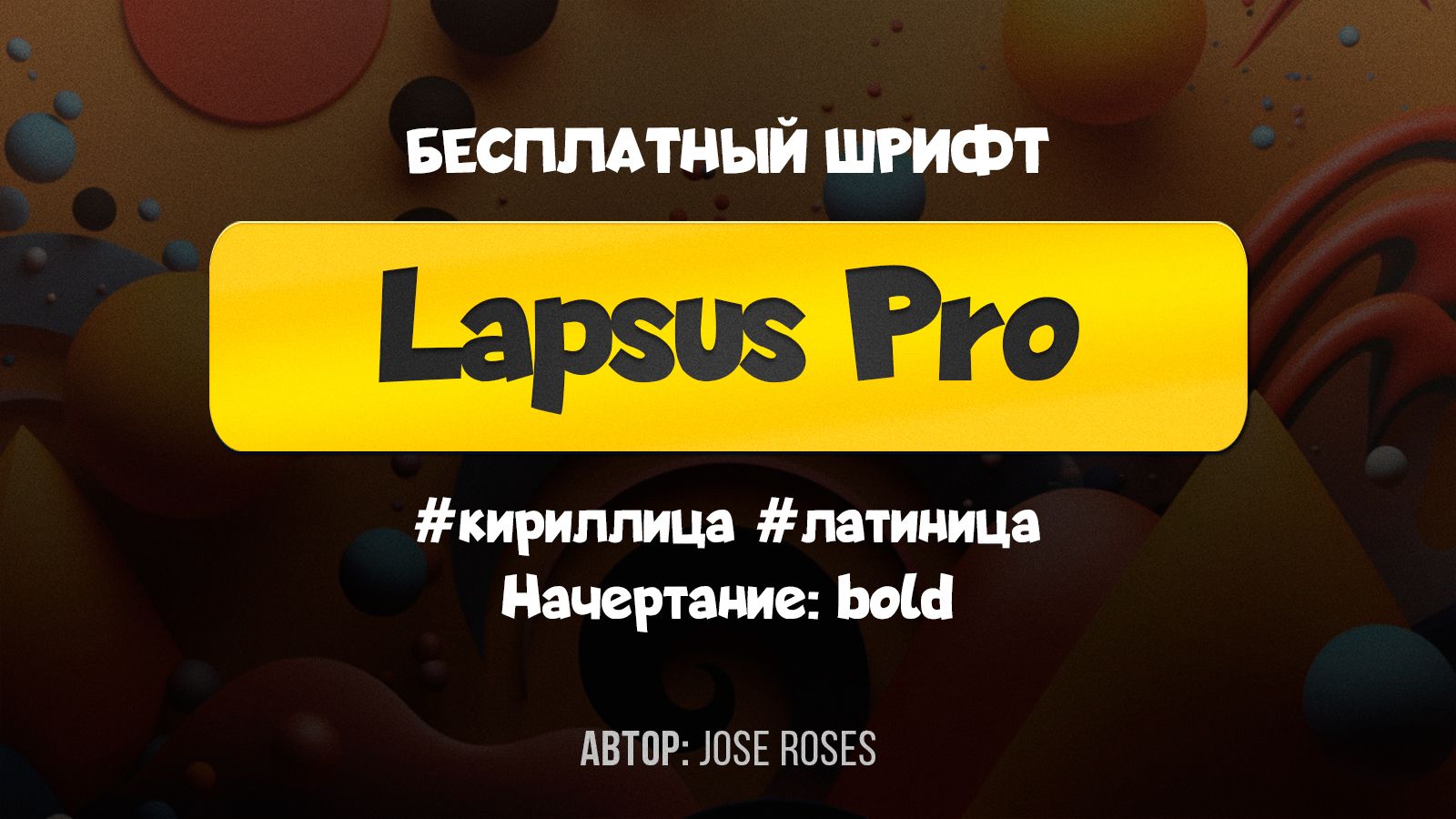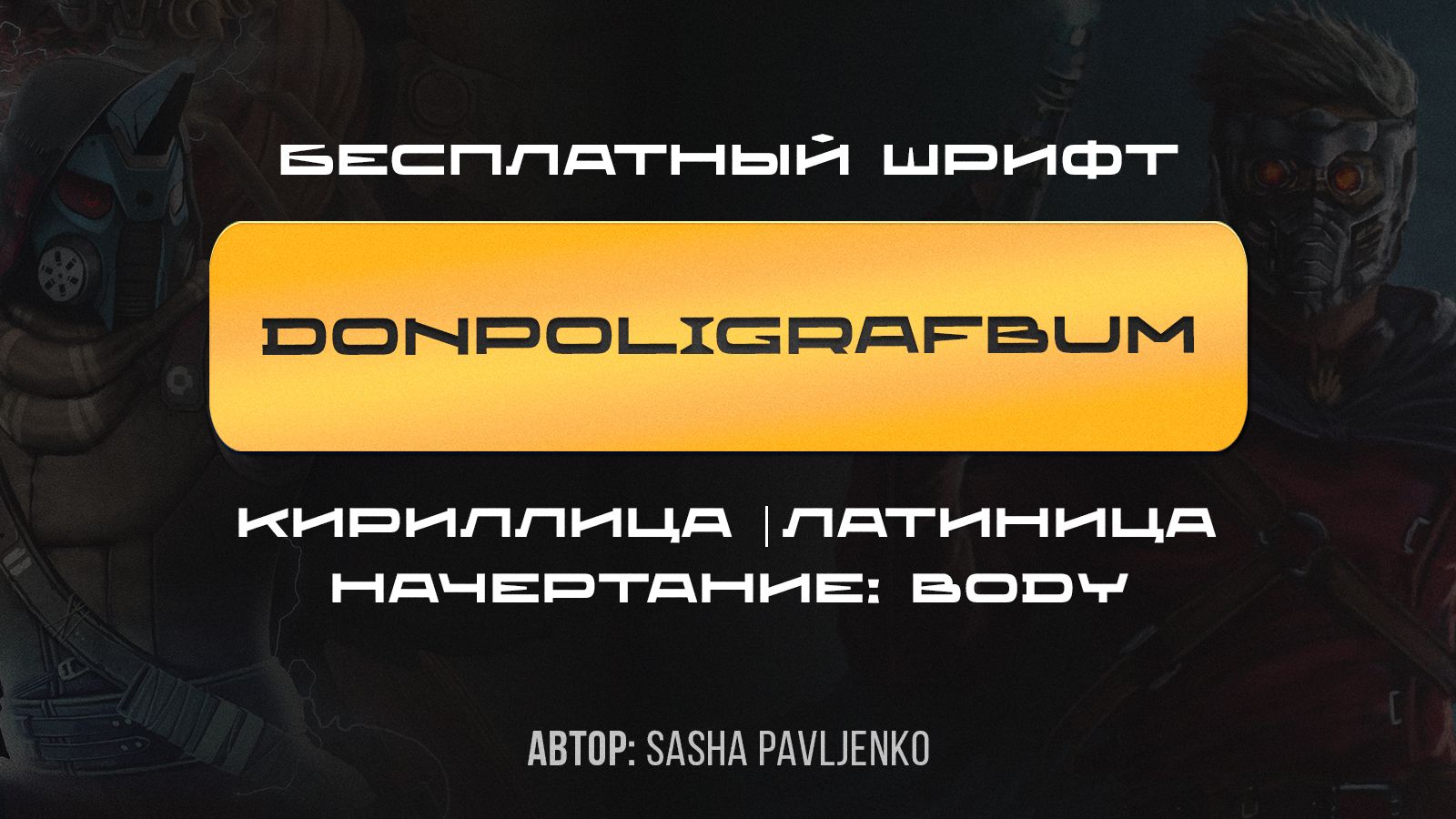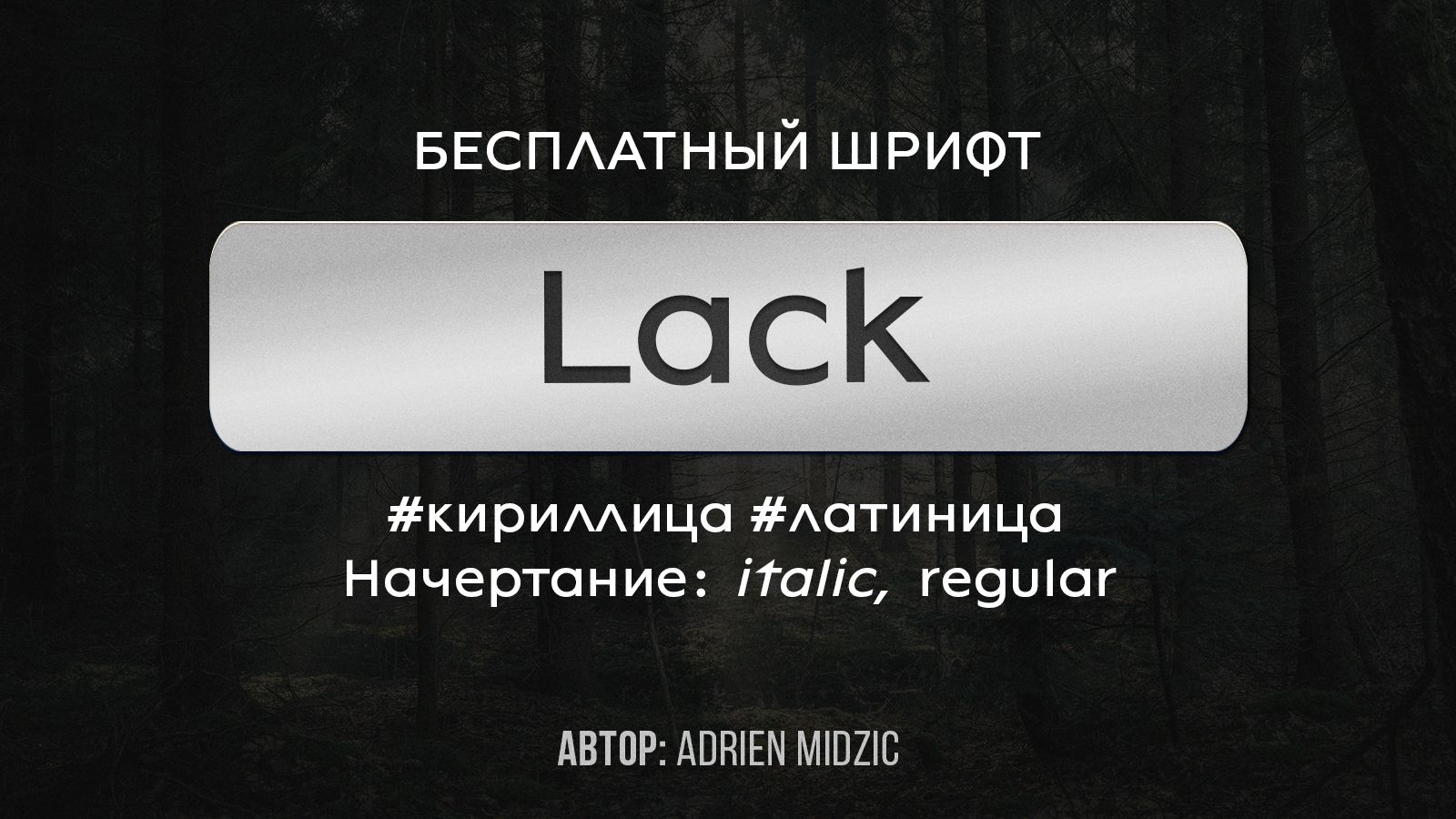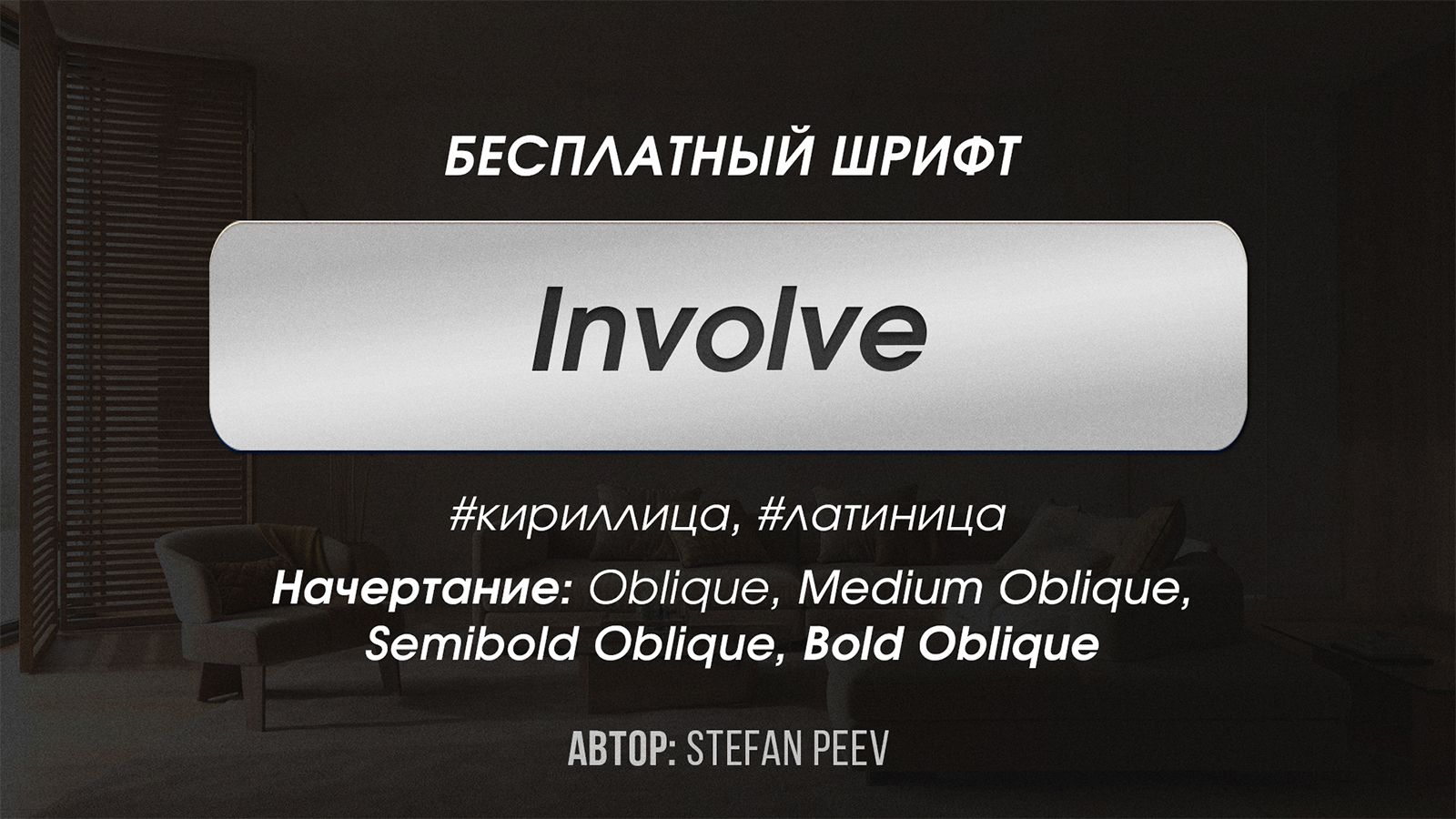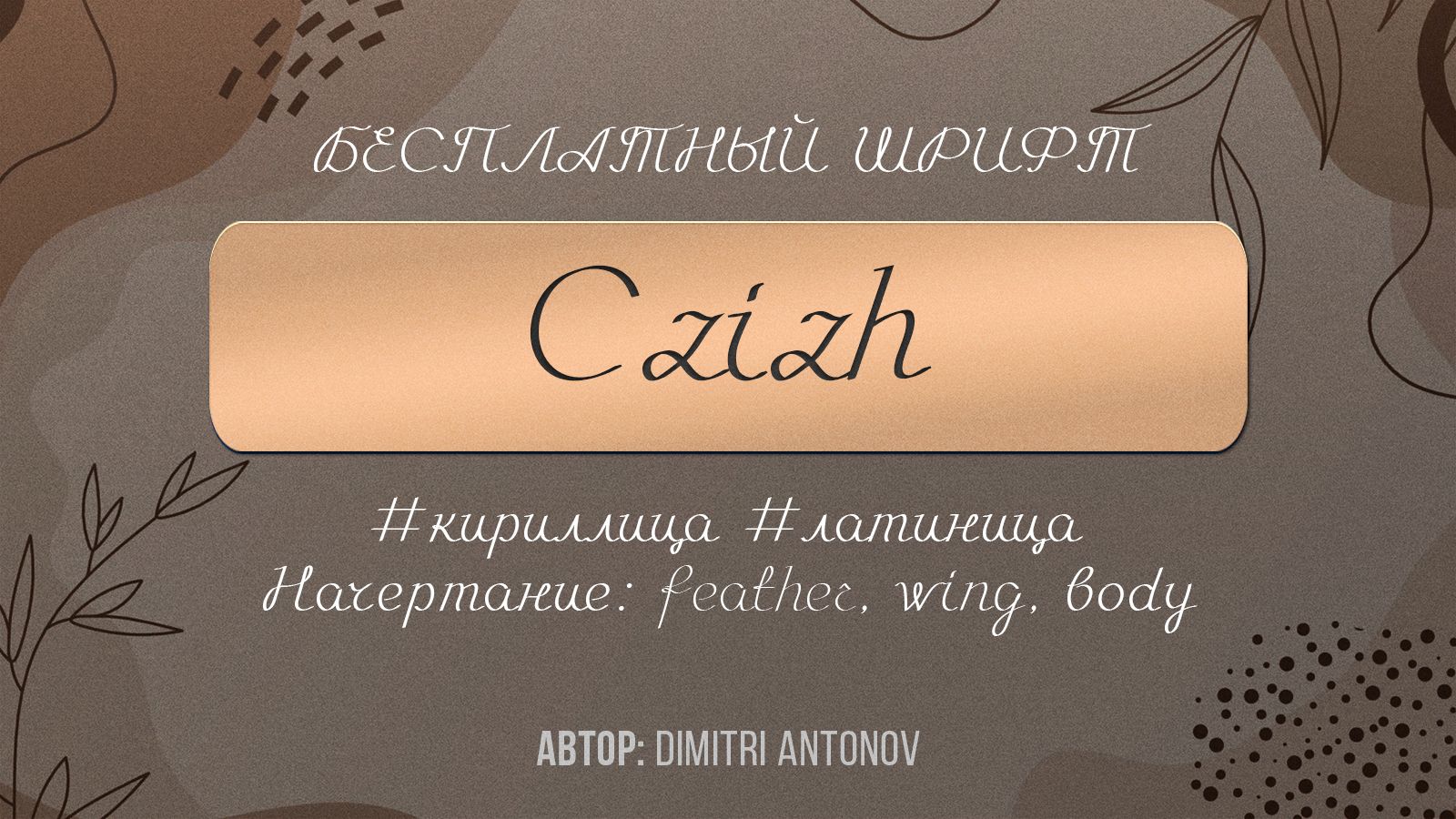
⚡️ 5 БЕСПЛАТНЫХ ШРИФТОВ, которые ОЖИВЯТ вашу карточку
1. Шрифт Lapsus Pro
Жирный, забавный и дружелюбный шрифт с расширенной языковой поддержкой.
Использование: Lapsus Pro отлично подходит для детских товаров, плакатов, книг, игр, футболок, поделок или просто в качестве стильного наложения текста на любое фоновое изображение.
2. Шрифт Czizh
Простой рукописный шрифт, передающий суть естественного почерка. В меру читаемый. Удобно использовать в паре с простым шрифтом.
Использование: подойдет для открыток или подписей.
3. Шрифт Lack
Многоязычный геометрический гротеск —это смелый и современный шрифт для ваших проектов.
Использование: хорошо работает как дисплейный шрифт, но также предназначен для работы с текстами любого размера.
4. Шрифт Donpoligrafbum
Декоративный шрифт в советском стиле, вдохновлённый брендом папирос «Наша марка».
Использование: отлично подойдет для плакатов, крупных заголовков и логотипов в агро- или машиностроительной отрасли, с намеком на советский стиль.
5. Шрифт Involve
Элегантный и современный геометрический шрифт без засечек, в котором органично сочетаются современная эстетика и геометрическая точность.
Использование: подходит как для длинных текстов, так и для крупных заголовков и логотипов. Универсален, подойдет даже для сложных дизайн-проектов (печать, веб- или моушн-дизайн)